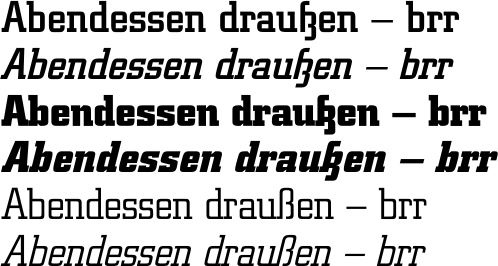
Schriftart mit besonderem „ß“ zu identifizieren
ich bin neu im Forum und suche für das nachfolgende Schriftbild die entsprechende Schriftart.
„WhatTheFont“ hat mir u.a. „Berthold City Medium“, „City Pro Medium“ und „Square Slabserif 711“ ausgespuckt, welche an und für sich passen, bis auf die besondere ſz-Ligatur.
Das Bild entstammt einem aktuellen Handzettel der portugiesischen „Porto-Bay-Hotels“.
Anzumerken ist, daß im selben Prospekt diese Schrift in einer etwas fetteren Variante verwandt wird, welche eben mit erster Variante bis auf das „ß“ identisch ist; dieses entspricht dem der o.g. Schriftarten.
Gelöst von Vitrioloel
diese besondere ß-variante findet man in einer schriftart namens centrum, einem (illegalen) klon der city von broderbund. eine legale alternative mit diesem (zugegeben: hübschen) ß habe ich nicht finden können.
Zwar gab es von Berthold und URW einen Medium-Schnitt mit eben jenem „ß“, im aktuellen Angebot ist dieses aber nicht enthalten. Allerdings gibt es bei den Franzis-Schriften eine „Citta“ welche der „City“ entspricht und bei den Berthold „Rechtsnachfolgern“ ist es wohl auch legitim diese zu nutzen.
Von meinen sechs Citta-Schriftschnitten enthalten vier (Normal, Italic, Bold, Bold-Italic) das gesuchte „ß“ die beiden anderen Schnitte (Small-Normal und Small-Italic) hingegen das neuere.
Wüßten Sie zufällig auch von einer arial-, helvetica-, oder times-new-roman-ähnlichen Schriftart, welche eine solche ſz-Ligatur (evtl. zzgl. eines »ſ«) enthält?
Bevor jetzt jemand lange sucht: die in der Liste aufgeführte Canapé  :biglove: bietet auf direktem Weg, soweit ich das sehen kann, kein alternatives ß. Ich kann lediglich ein z per ss02 in ein ʒ verwandeln. Stelle ich ein ſ davor, wird es mit dem ʒ zur gewünschten ß-Form ligiert. Kodierungstechnisch ist das natürlich ungünstig. Ich müsste Straſʒe bzw. Straſze schreiben, um die Form zu erreichen.
:tuschel: Ließe sich da vielleicht was für das nächste Update machen? :bow: